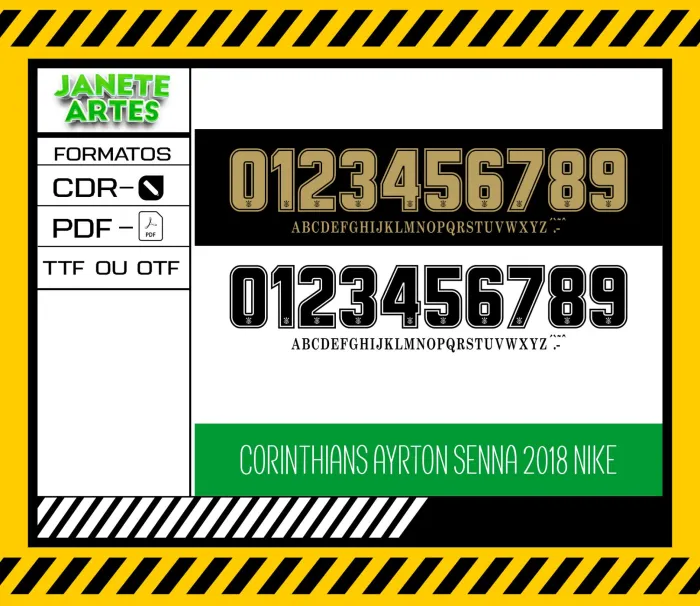
Apaixone-se pela história do Corinthians em cada detalhe
Já imaginou vestir a camisa do seu time de uma forma totalmente personalizada? Foi assim que um grupo de torcedores do Corinthians decidiu criar algo exclusivo para mostrar a paixão pelo time. A Fonte de Time Tipografia Corinthians 2018 traz aquele estilo único e reconhecível que marcou os momentos gloriosos de 2018. A emoção vai além do campo, refletindo no design e na forma como você pode expressar seu amor pelo Corinthians!
O que você recebe e como usar a Fonte de Time Tipografia Corinthians 2018
- Tipografia inspirada na fonte usada pelo Corinthians em 2018, para criar camisetas, camisas e blusas exclusivas.
Ideias e dicas para aplicar sua fonte
- Personalize camisetas para uma turma de amigos torcedores ou um evento especial.
- Crie presentes únicos para fãs do Corinthians, seja para aniversário ou comemorações.
- Combine com cores tradicionais do time, como preto e branco, para uma peça autêntica.
- Use em camisas de treino, blusas informais ou camisetas de lazer para mostrar sua paixão.